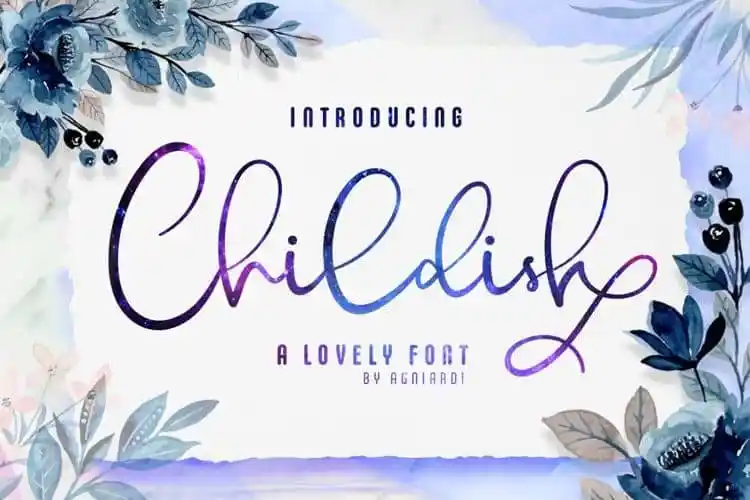
Childish Calligraphy Font – Download Grátis
A Childish Calligraphy Font é uma elegante escolha para quem procura um estilo artístico que se encaixa perfeitamente entre o antigo e o moderno. Com seus traços fluidos e delicados, ela é ideal para projetos como cartões de convite de casamento, cartinhas de felicitações ou até mesmo para criar designs para redes sociais e marcas de marca. Esta fonte traz uma atmosfera descontraída e divertida com alternativas gírias quase em cada letra minúscula. Isso lhe dá a oportunidade de criar designs têxteis, cupcakes ou simplesmente se entreter. Para acessar todas as alternativas stylistic do OpenType, você precisará de um programa que suporte essas funcionalidades, como Adobe Illustrator, Adobe Photoshop, CorelDraw e Microsoft Word. Uma fonte perfeita para quem busca criatividade e sofisticação em sua arte digital.